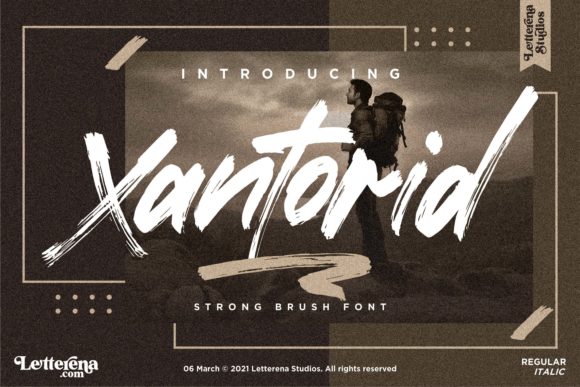
Creativefabrica Xantorid Font
[Creativefabrica] Xantorid Font
Xantorid - это крутой, грубый шрифт для дисплея.
Добавьте этот шрифт к каждой вашей идее городского дизайна, и они оживут.